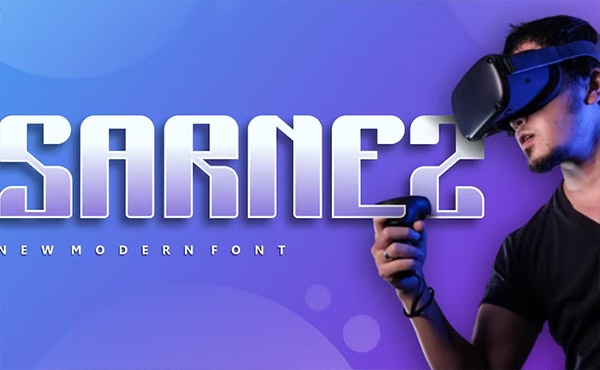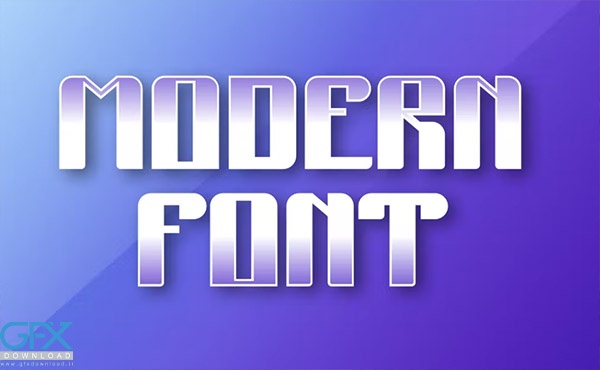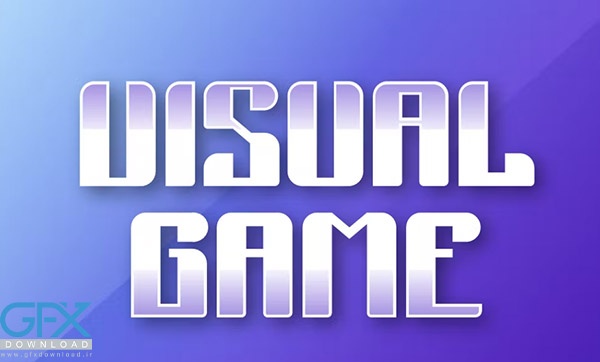
یک فونت مدرن و یک فونت نمایشگر برجسته و معتبر است. این فونت برای هر پروژه برندسازی مانند لوگو، چاپ تی شرت، esport و بسیاری موارد دیگر مناسب است. برجسته در طیف گسترده ای از زمینه ها. برای دانلود فونت Sarnez از جی اف ایکس دانلود به ادامه مطلب مراجعه کنید.